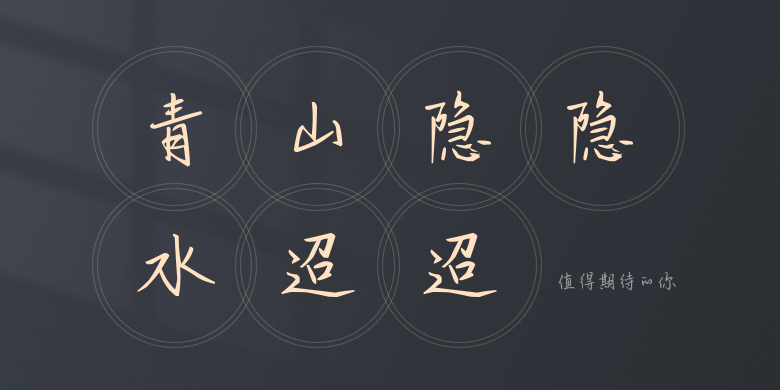
值得期待的你
值得期待的你,这款字体结构工整、笔画清晰,兼顾美观与易读性,适用于标题、正文、海报、包装、LOGO 等多种场景。字形优雅稳定,风格百搭耐看,适配日常排版与创意设计,让文字呈现更舒适、更具质感。值得期待的你一笔一画,皆是细节,以均衡的比例、流畅的线条打造舒适视觉体验,字形端正大气,风格简约现代。无论是商业设计、品牌宣传还是日常排版,都能轻松驾驭,让文字更有格调与力量。值得期待的你字体下载。